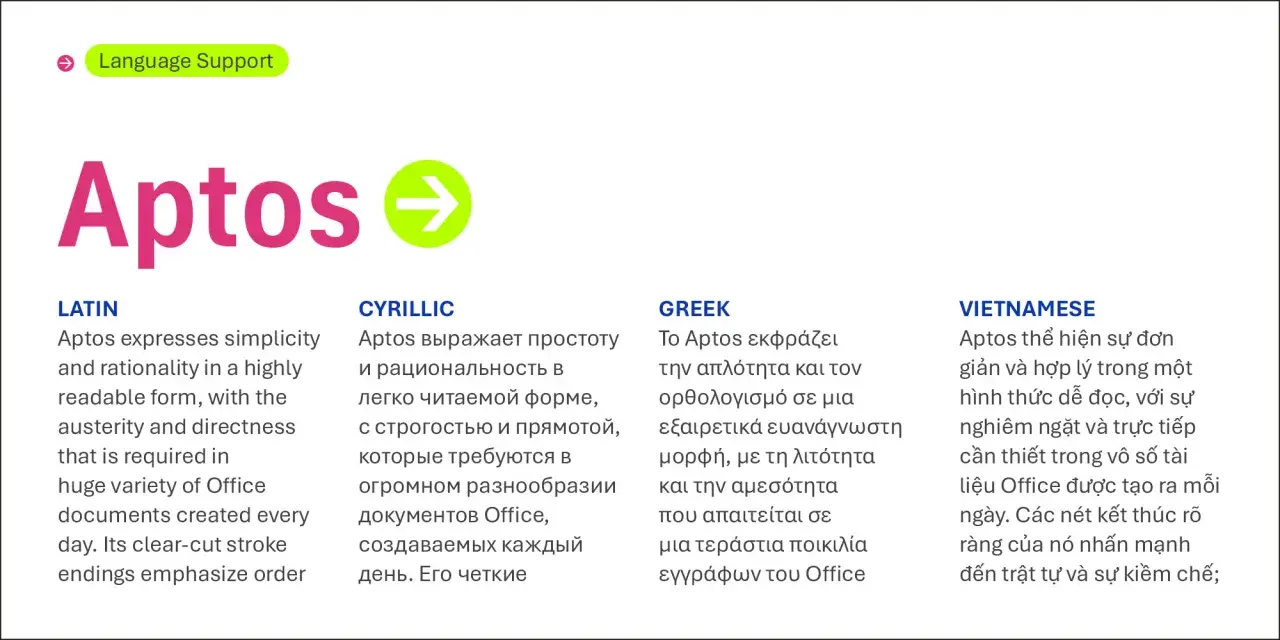
Aptos – nowy domyślny font Office. Czy to dobry wybór?
Czcionka Aptos, prezentowana w wielu językach, podkreśla prostotę i czytelność.
Aptos to dziś jeden z najbardziej praktycznych krojów w ekosystemie Microsoft: neutralny, czytelny i zaprojektowany tak, by dobrze działał na ekranach o wysokiej rozdzielczości. W praktyce czcionka Aptos stała się domyślną bazą dla dokumentów, prezentacji i arkuszy, dlatego warto wiedzieć, kiedy faktycznie pomaga, a kiedy lepiej jej nie przeceniać. W tym tekście pokazuję też, jak wygląda jego rodzina, jak ustawić go w Office i jak myśleć o nim w projektach stron internetowych oraz e-commerce.
Aptos to domyślny krój Office, który stawia na czytelność i neutralność
• Microsoft wprowadził Aptosa jako następcę Calibri w środowisku Office.
• To krój bezszeryfowy, zaprojektowany z myślą o pracy na ekranie i czytelnym układzie treści.
• Rodzina obejmuje różne grubości i wersje do nagłówków, tabel oraz ciasnych układów.
• Najlepiej sprawdza się w dokumentach biznesowych, prezentacjach, arkuszach i interfejsach.
• Na stronie internetowej wymaga dobrego fallbacku, bo nie każdy użytkownik ma go lokalnie.
Czym jest Aptos i dlaczego Microsoft postawił właśnie na ten krój
Według Microsoft Learn, Aptos to precyzyjny, współczesny krój bezszeryfowy inspirowany szwajcarską typografią z połowy XX wieku. W praktyce oznacza to ostro zarysowane zakończenia kresek, wyraźne połączenia łuków z prostymi liniami i mniejsze wrażenie „zlepiania się” liter, co bezpośrednio poprawia czytelność. To nie jest font, który ma krzyczeć; jego zadanie jest prostsze i trudniejsze zarazem: ma pozwolić treści mówić pierwszoplanowo.
Ważny jest też kontekst zmiany. Microsoft szukał następcy dla Calibri, bo sposób pracy z dokumentami zmienił się wraz z wyższą rozdzielczością ekranów i innymi oczekiwaniami wobec typografii. Aptos ma być bardziej neutralny, bardziej uporządkowany i lepiej skalować się w codziennych materiałach firmowych. Da się go użyć zarówno w tekście podstawowym, jak i w nagłówkach, co daje mu sporą elastyczność.
W mojej ocenie to właśnie ta powściągliwość jest jego największą zaletą. Aptos nie próbuje przejąć charakteru całej strony czy dokumentu, tylko buduje solidne tło dla informacji. Z takiej konstrukcji wynikają różne odmiany i grubości, które warto poznać zanim zacznie się go wdrażać w konkretnym projekcie.
Jak wygląda rodzina Aptosa i które odmiany mają realne znaczenie
W praktyce nie mówimy o jednym pliku, ale o rodzinie krojów. Microsoft przewiduje kilka wag i wersji, które rozwiązują różne problemy składu: od zwykłego tekstu, przez slajdy, po ciasne tabele. Microsoft Learn opisuje Aptosa jako rodzinę z sześcioma wagami, od Light do Black, oraz z komplementarnymi stylami pochylonymi, więc nie trzeba traktować go jak jednego „domyślnego fontu do wszystkiego”.
Odmiana Najlepsze zastosowanie Co daje Kiedy uważać
Regular Tekst podstawowy, dokumenty, artykuły Najspokojniejszy rytm czytania i neutralny wygląd Nie buduje mocnego akcentu wizualnego
Light Lżejsze slajdy, premium layouts, krótkie hasła Więcej oddechu i delikatniejszy ton W małych rozmiarach może tracić na wyrazistości
Semibold Nagłówki, dashboardy, sekcje z hierarchią Wyraźniejszy podział informacji Łatwo przesadzić i zrobić układ zbyt ciężki
Black Okładki, hero, krótkie tytuły Silny kontrast i mocna obecność Nie nadaje się do dłuższych akapitów
Condensed Tabele, Excel, wąskie kolumny, panele admina Mieści więcej treści w ograniczonej szerokości Zbyt ciasny skład męczy wzrok
Display Bardzo duże nagłówki i otwarcia sekcji Lepsza czytelność przy dużych rozmiarach i większa „krystaliczność” formy Nie powinien zastępować zwykłej wersji w tekście bieżącym
Warto też pamiętać o jednym technicznym detalu: kursywa Aptosa jest oblique, czyli to lekko pochylona forma liter prostych, a nie klasyczna odręczna italika. To drobiazg, ale w dokumentach firmowych i prezentacjach wpływa na odbiór całej hierarchii. Z tego powodu Aptos sprawdza się najlepiej wtedy, gdy świadomie wybierasz wagę i wersję, zamiast wrzucać wszędzie tę samą odmianę.
Skoro wiadomo już, jak wygląda rodzina, następne pytanie jest prostsze: gdzie ten krój naprawdę robi różnicę, a gdzie jest tylko poprawnym, ale mało wyrazistym wyborem.
Gdzie Aptos sprawdza się najlepiej w praktyce
Ja najczęściej wybieram Aptosa tam, gdzie treść ma być pierwszoplanowa, a typografia ma pomagać, nie dominować. To krój bardzo dobry do pracy, bo nie odwraca uwagi od informacji, a jednocześnie trzyma układ w ryzach.
• Dokumenty Word - raporty, procedury, oferty, notatki projektowe i materiały dla klienta. Neutralność ułatwia czytanie dłuższych bloków tekstu.
• Prezentacje PowerPoint - slajdy z prostą hierarchią informacji, gdzie Light, Semibold i Black mogą budować wyraźny rytm bez nadmiaru ozdobników.
• Arkusze Excel - zwłaszcza w wersjach Condensed, kiedy każda kolumna ma znaczenie i trzeba upchnąć sporo danych bez wizualnego chaosu.